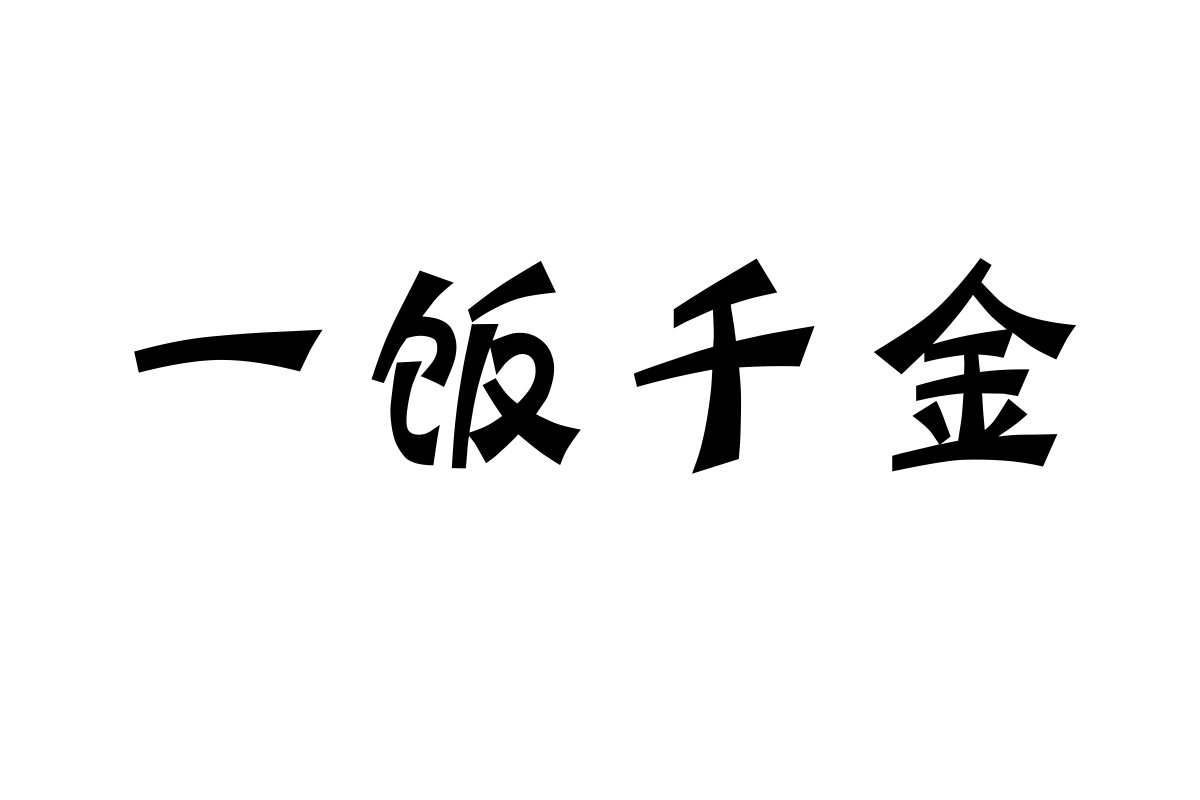
汉仪蝶语体简是一款现代中文字体,由汉仪字库设计制作。这款字体具有独特的设计风格,笔画流畅自然,结构简洁大方。它适用于各种印刷品和数字媒体,如报纸、杂志、书籍、广告、网页等。汉仪蝶语体简的字体特点包括:
1. 字形简洁大方,线条流畅自然。
2. 笔画粗细适中,易于阅读和书写。
3. 结构紧凑,整体感强。
4. 适用于多种场合,如正式文件、商业广告、文艺创作等。